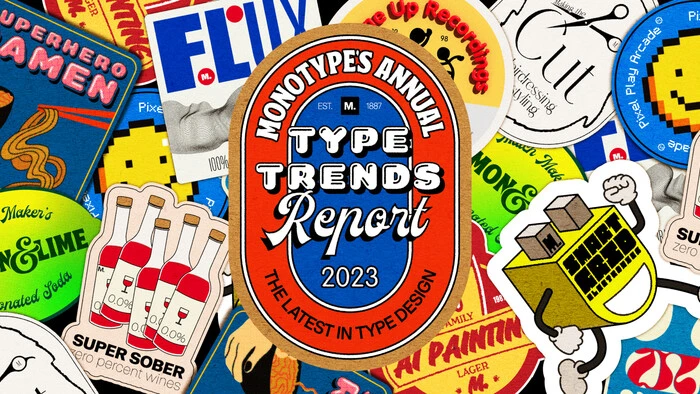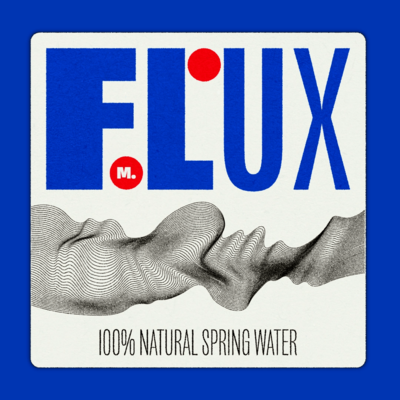
Tendências tipográficas para 2023.
O relatório anual de tendências.
Nossas vidas e nosso trabalho de design estão constantemente em movimento. Este relatório é uma oportunidade para reflexão e projeção, uma parada ao longo do caminho, para ajudá-lo a recarregar-se e planejar-se para o próximo ano.
Tendências tipográficas para 2023.
Detecção de tendências tipográficas do Monotype Studio.
Match Maker.
Diversity, variety, and powerful pairing in visual form.
Smart Grid.
Grids are the main attraction, but they’ve been softened and cut with precision and sophistication.
Pixel Play.
Using pixel forms by adding moments of interest or planting their digital-focus flag in the ground. Diversity, variety, and powerful pairing in visual form.
Making The Cut.
Treatments often add sparkle, motion, and visual interest to an otherwise plain sans serif.
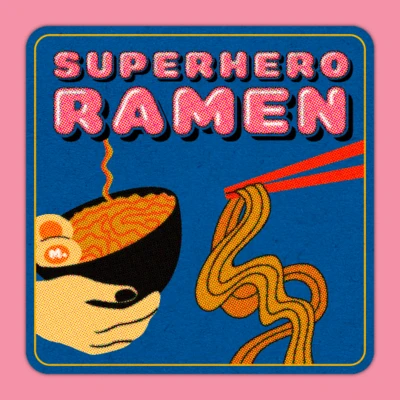
Superhero.
Bursting onto the scene with outlined or shadowed forms, often tilted, skewed, or curved into perspective.
Flux.
Anything that moves is catching eyes these days. Think animation and variable fonts.
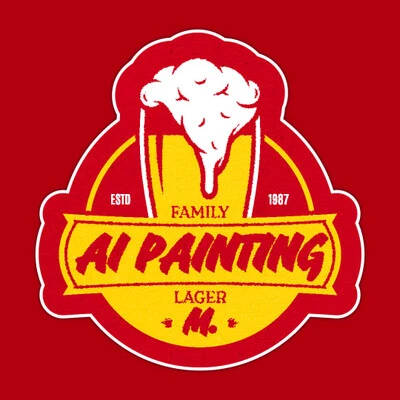
AI Painting.
AI image generation, but with letterforms.
Liquify.
The more liquified, the better, but legibility hangs on by a thread in this trend.
Volume up.
Are 3D modeling and animation now graphic design?